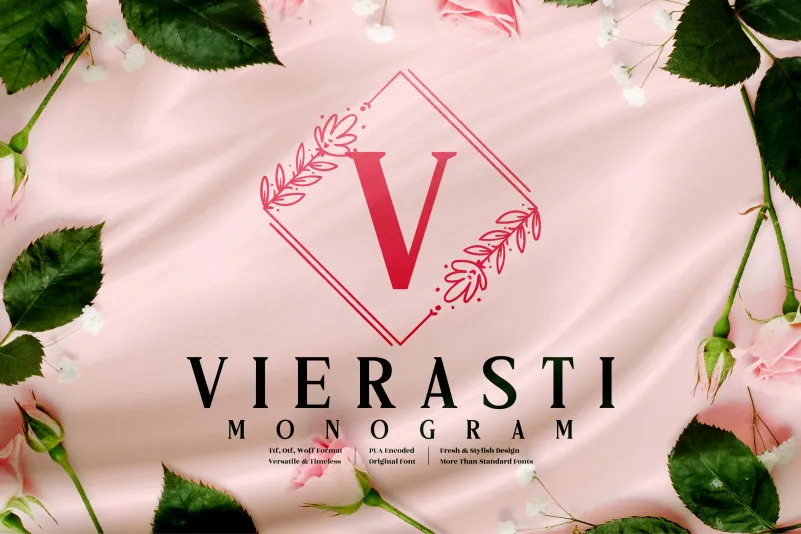
A Vierasti Monogram Font é uma opção elegante para estilos de fontes display que valoriza a beleza e os detalhes. Ela incorpora ornamentos de folhas luxuosas, trazendo um toque sofisticado e elegante para qualquer projeto gráfico. Este tipo de fonte é perfeito para criar cartões de saudação encantadores, artes de selo impressionantes, postagens em redes sociais impactantes e logotipos distintivos. A Vierasti Monogram Font também traz um toque atraente aos seus designs de cartas personalizadas, tornando-as ainda mais únicas e memoráveis. Seja você designer ou amante do design, essa fonte é certamente uma escolha incrível para dar um destaque especial em suas criações gráficas.